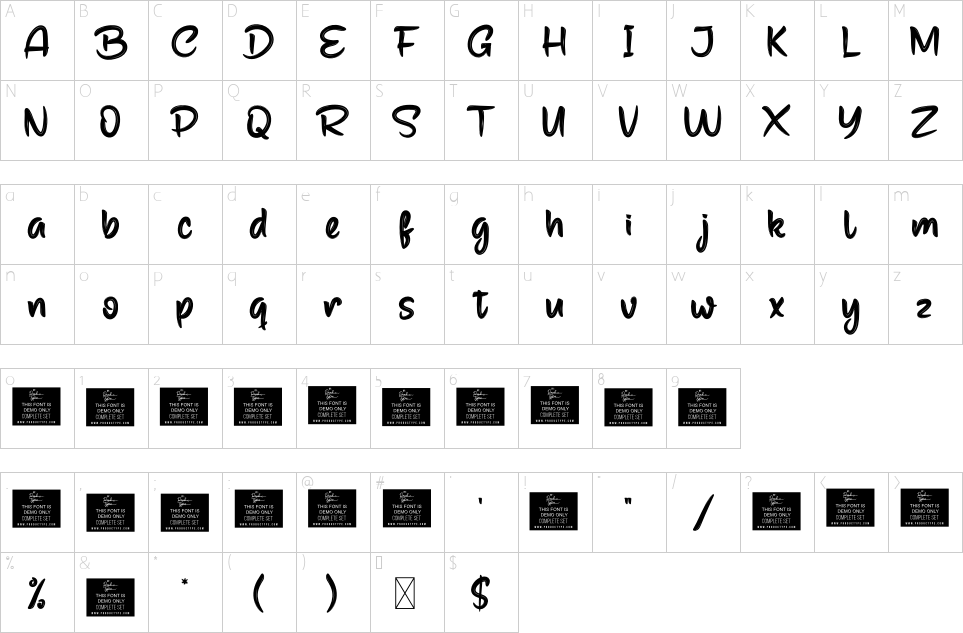
A fonte ‘Mayor Font’ é uma escolha elegante para designers gráficos em busca de uma fonte moderna e minimalista. Desenvolvida pelo designer produtype, esta fonte vem em versões para Windows e Mac e tem sido descarregada 1.277 vezes. Com uma estética simples que se ajusta a um vasto espectro de projetos, a Mayor Font é uma ótima opção para aplicativos de design gráfico, websites e até mesmo para criação de materiais educativos. Se você está procurando uma fonte moderna que não comprometa seu trabalho com excesso de personalização, a Mayor Font é uma fonte que merece ser explorada.